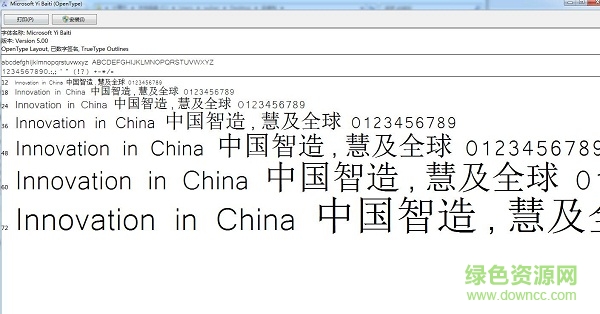
microsoft yi baiti bold
microsoft yi baiti bold字體是一款纖細(xì)美觀的微軟字體,筆畫簡(jiǎn)潔,字形清新,顯示效果也會(huì)非常好,適合用于網(wǎng)頁(yè)設(shè)計(jì)或平面設(shè)計(jì),有需要者歡迎免費(fèi)下載!
microsoft yi baiti字體特點(diǎn)
該字體細(xì)節(jié)表現(xiàn)完整,引擎渲染的效果好,且字庫(kù)完整,易于閱讀。